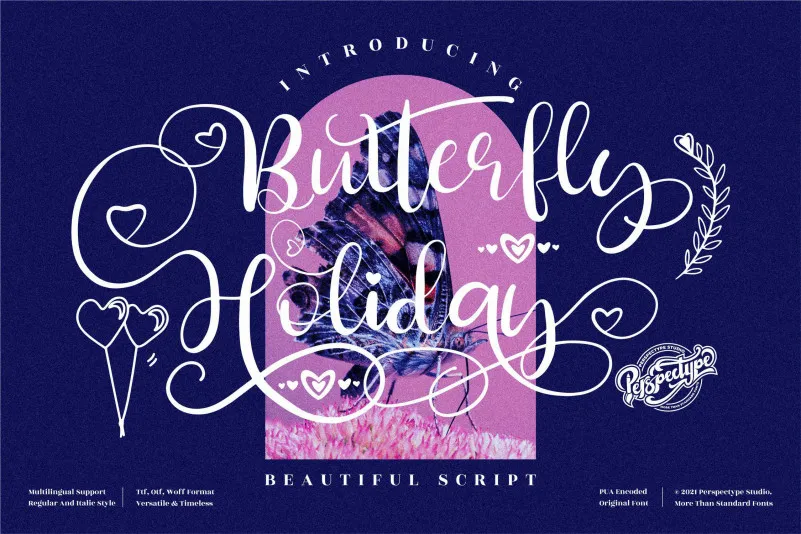
Butterfly Holiday Font – Fonte Grátis
Butterfly Holiday Font
Esta é uma fonte script romântica e delicada, perfeita para personalizar textos de forma elegante. Ela foi cuidadosamente elaborada e detalhada, ideal para adicionar valor a qualquer projeto. Este design especializado tem o potencial de tornar seu texto ainda mais atraente. Uma das características interessantes desta fonte é que ela é PUA encodada, o que significa que você pode acessar todos os caracteres e swashes facilmente. Ainda não experimentou a magia da Butterfly Holiday Font? Essa é uma excelente escolha para quem procura uma fonte script de alta qualidade. Ela oferece um nível único de personalização, tornando-a uma opção ideal tanto para projetos pessoais quanto profissionais. Com sua natureza delicada e romântica, esta fonte certamente enriquecerá qualquer projeto, seja em impressões digitais ou gráficos manuscritos. Adquira a Butterfly Holiday Font hoje e descubra por si mesmo o fascínio desta fonte única e versátil.